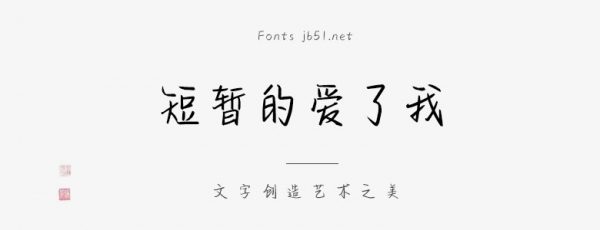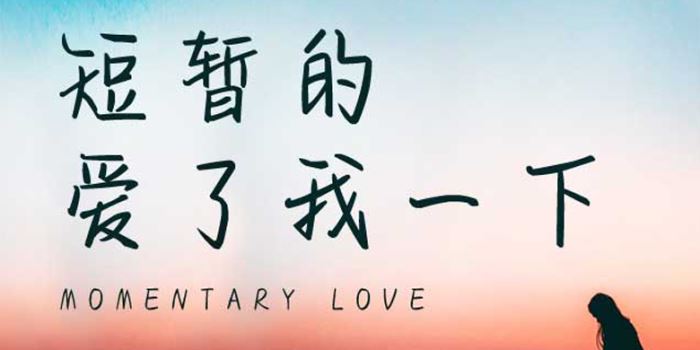
方正手迹-短暂的爱了我一下
方正手迹-短暂的爱了我一下由方正字库王航设计师出品的艺术字体,该字起收笔触表现明显,字形上松下紧,韵味十足,适合应用于艺术设计、平面宣传设计、网页设计,书法等领域。
短暂的爱了我一下这款字体用笔考究,起收笔触表现明显,字形上松下紧,韵味十足。适用于文艺类的书刊、品牌广告和产品包装设计,以及社交网络的个性化用字。。